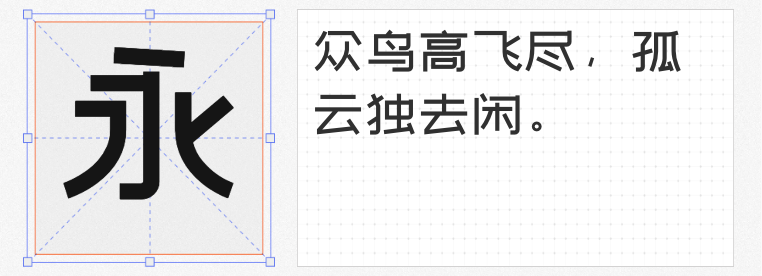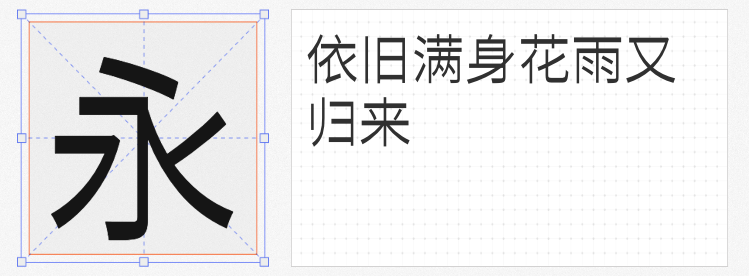
在海报设计的视觉战场中,字体是传递品牌调性的核心武器。如何平衡辨识度与艺术性?如何用免费字体打造高级感?以下四款经过实战检验的免费商用字体,将为你解锁海报设计的无限可能。
1. 站酷小薇LOGO体
这款由站酷设计师李宜坦创作的字体,以剑身为灵感重构笔画形态。修长的字形中暗藏锋芒,通过删减冗余笔画实现极简美学,却依然保持98%的识别率。在科技产品海报中,其金属质感的笔画能瞬间强化未来感;运动品牌宣传中,倾斜的笔画角度自带速度张力。建议搭配深色背景使用,让字体的锋芒穿透视觉屏障。
2. 站酷文艺体
由刘兵克团队打造的这款字体,用0.3mm的笔触差异构建文艺宇宙。略扁的字形自带慵懒气质,圆角处理与直角转折的碰撞,恰似理性与感性的对话。在咖啡厅海报设计中,搭配手绘插画能营造治愈氛围;文化展览宣传中,与宋体混用可创造新古典主义美学。特别适合需要传递温暖感的春日主题海报。
3. 仓耳非白 W04
这款字体,用极致的黑白对比重构了汉字结构。直角转折与直线撇捺构建出建筑般的秩序感,圆形点画又巧妙软化了机械感。在汽车广告中,能完美承载金属光泽;极简风格海报里,与留白配合可创造高级呼吸感。![]()
4. 寒蝉无机体 Regular
基于思源黑体的逆差改造,这款字体颠覆了传统黑体的视觉平衡。中部膨胀的笔画设计形成独特的视觉引力。在音乐节海报中,其叛逆的造型与涂鸦元素天然契合;潮牌宣传中,与故障艺术结合可制造数字时代的冲突美学。